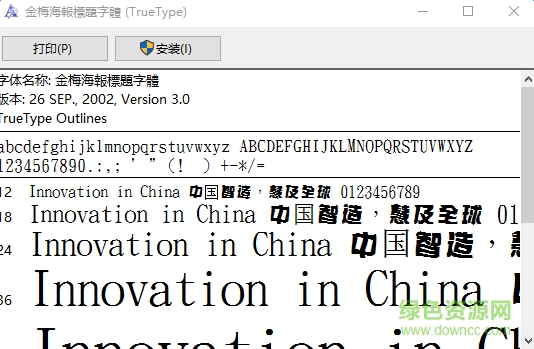
金梅海報(bào)標(biāo)題字體是金梅字庫(kù)中的一款具有藝術(shù)風(fēng)格的電腦字體,用于廣告設(shè)計(jì)、藝術(shù)設(shè)計(jì)等方面是最合適不過(guò)的,當(dāng)然如果大家喜歡這款字體,不管用在什么方面都是可以的,歡迎大家來(lái)綠色資源網(wǎng)下載。
金梅海報(bào)標(biāo)題字體字形大氣美觀,筆法比較有特色,不拘一格,是一款很不錯(cuò)的藝術(shù)字體,實(shí)用性也很強(qiáng),大家可以來(lái)綠色資源網(wǎng)免費(fèi)下載使用。